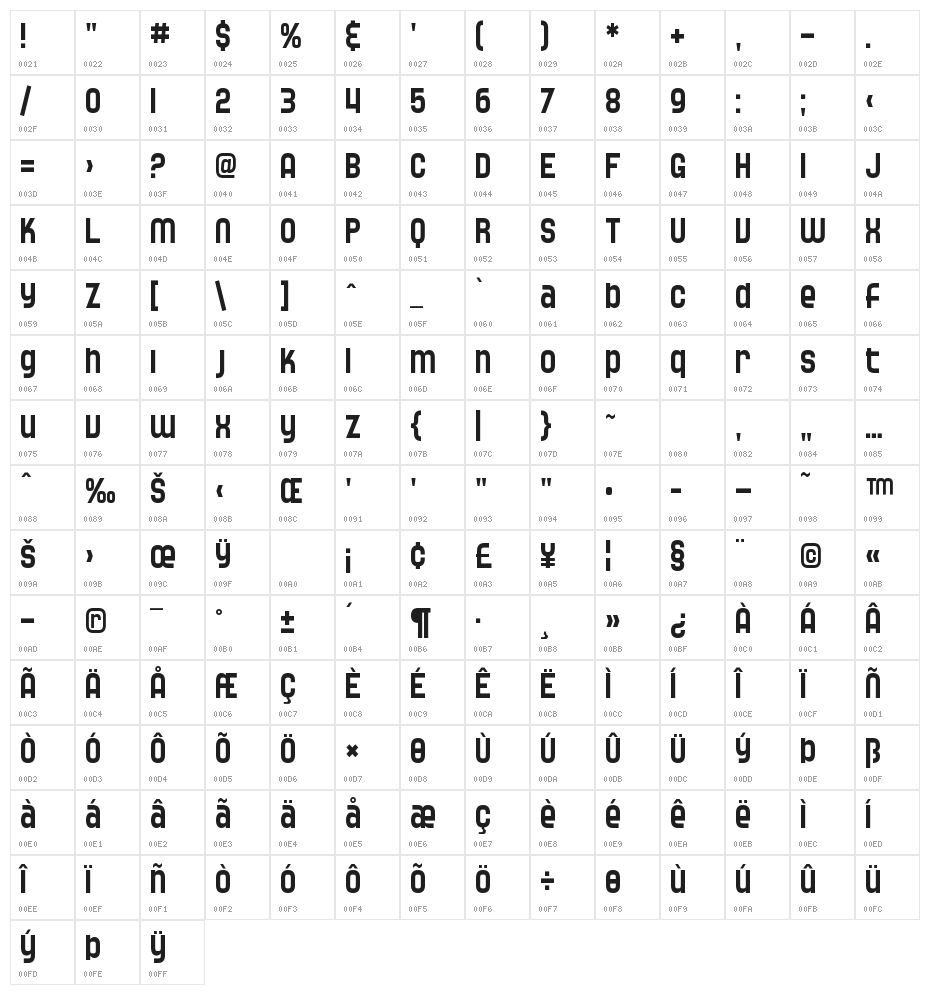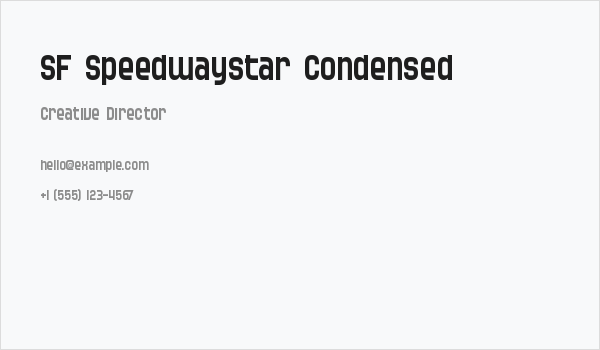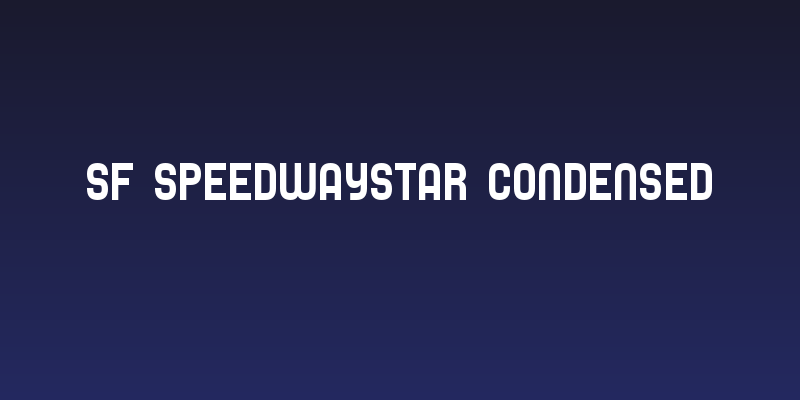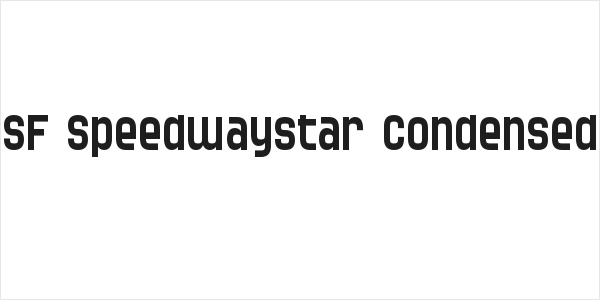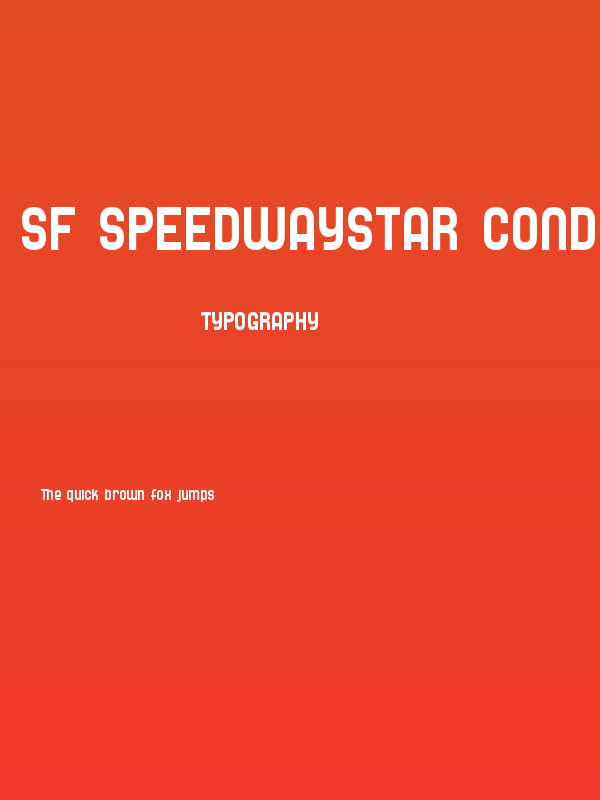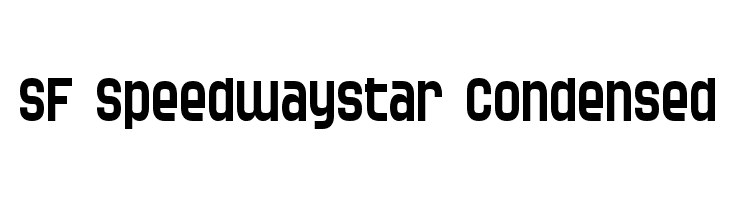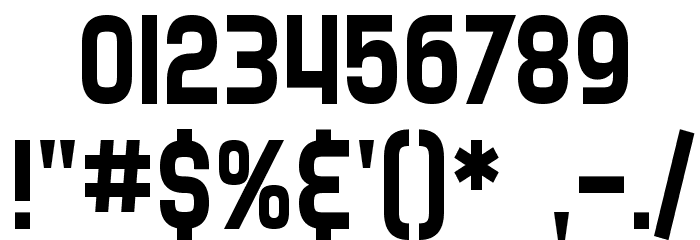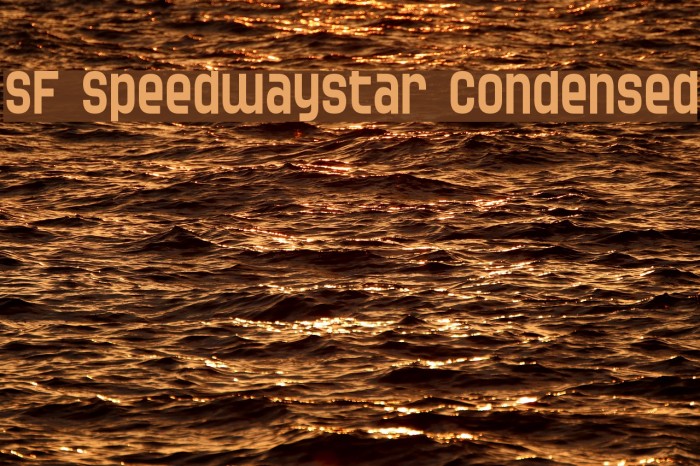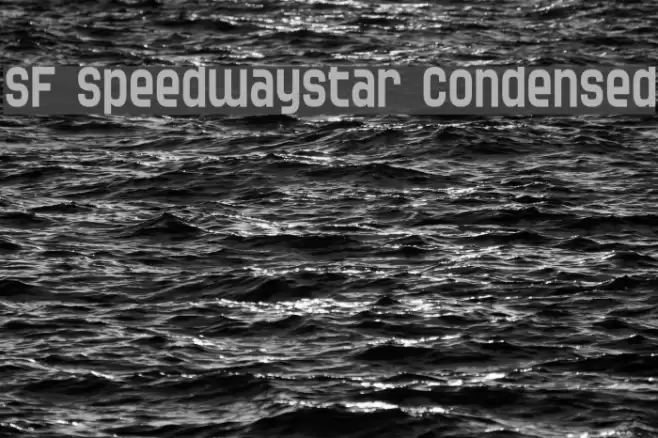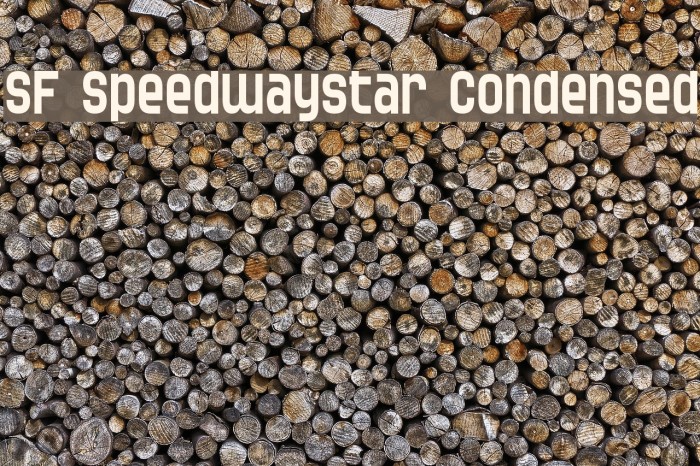
SF Speedwaystar Condensed Font
| おすすめプロジェクト | This font is perfect for projects that require a strong visual impact, such as posters, banners, and branding materials. Its modern style makes it suitable for tech-related designs, sports branding, and dynamic advertising campaigns. |